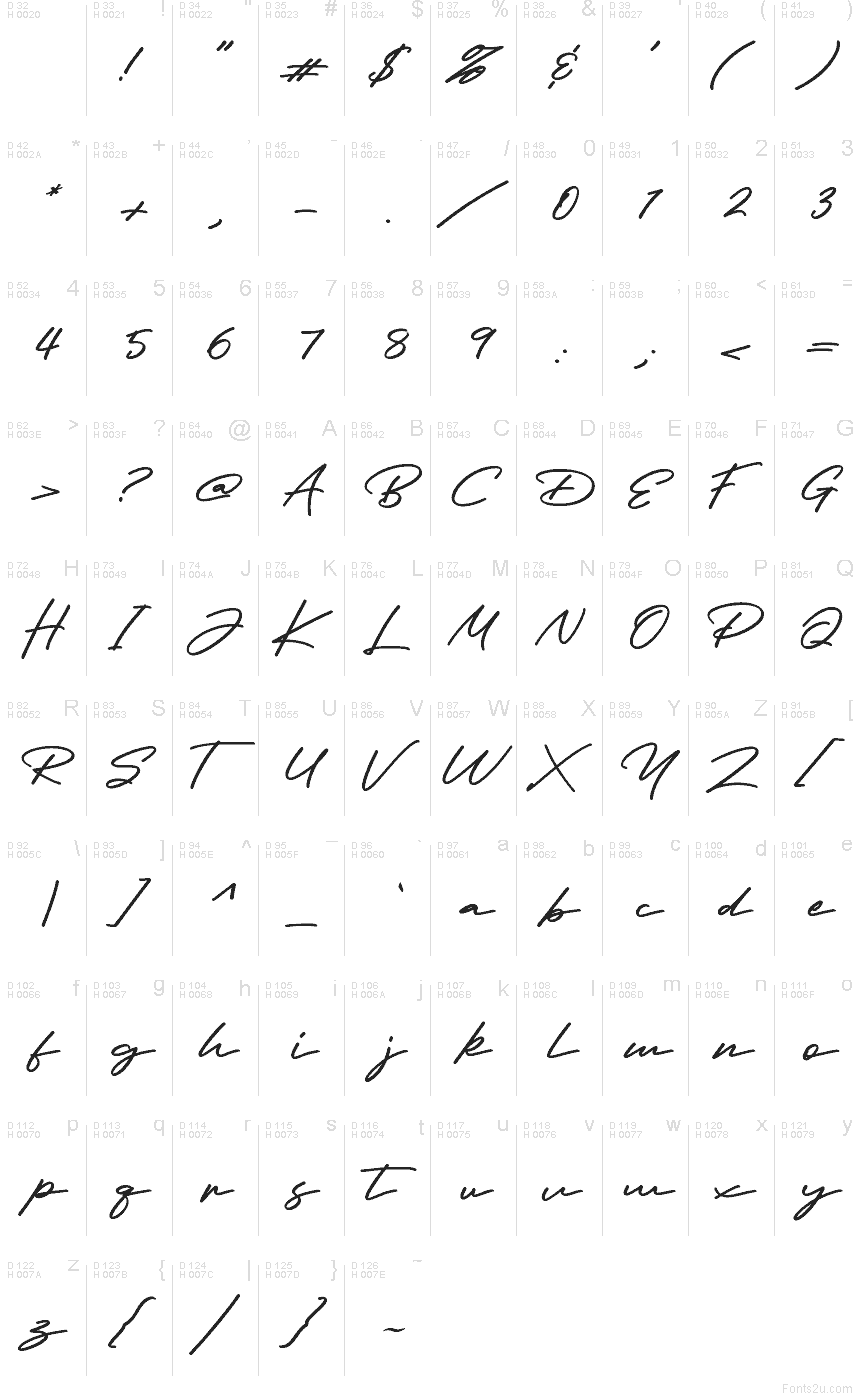
Wishful Melisande di Rinaldo Hasibuan è un font script scritto a mano gratuito, caratterizzato da tratti lunghi e avvolgenti e da un ritmo corsivo sciolto che scorre fluido sulla linea. Il lettering risulta arioso e continuo, con ascendenti alte e tratti trasversali estesi che gli donano un carattere personale, simile a una firma, lontano dai rigidi finali a pennello.
Questo dinamismo lo rende ideale per loghi di boutique, cartoleria per matrimoni, packaging di prodotti, header per i social media e grafiche con citazioni, dove una singola riga di testo può reggere l'intera composizione. Si adatta perfettamente anche ad accenti di branding e titoli di inviti, poiché le connessioni allungate creano un elegante slancio orizzontale che riempie lo spazio senza risultare rigido.